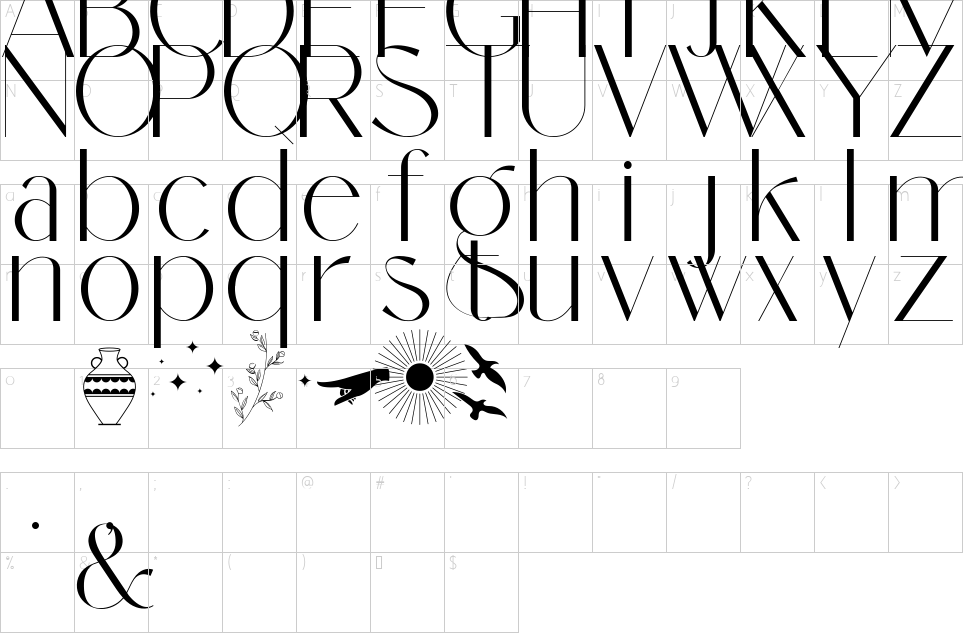
A Dolce Gargia é uma fonte elegante e confortável que se destaca por sua harmoniosa combinação de formas arredondadas e linhas leves. Desenvolvida pelo designer indizível, a Dolce Gargia oferece um toque sofisticado para qualquer projeto digital ou impressão. Suas linhas fluidas permitem uma escrita suave e legível, tornando-a ideal tanto para textos de marketing quanto para design gráfico detalhado. Para usuários Windows e Mac, a Dolce Gargia font é fácil de instalar e adaptar à sua necessidade específica de projeto. Com mais de 377 downloads, a Dolce Gargia mostra a sua utilidade e qualidade em uma variedade de contextos. Seja você um designer gráfico experiente ou alguém iniciando nesta área, a Dolce Gargia é uma opção confiável para adicioná-la ao seu arsenal de ferramentas. A fonte não só se destaca por sua praticidade de uso mas também pela sua capacidade em dar um toque especial aos seus projetos. Ideal tanto para texturas modernas quanto para gráficos tradicionais, a Dolce Gargia oferece uma opção confiável e versátil para aqueles que buscam fontes de alta qualidade gratuitamente.